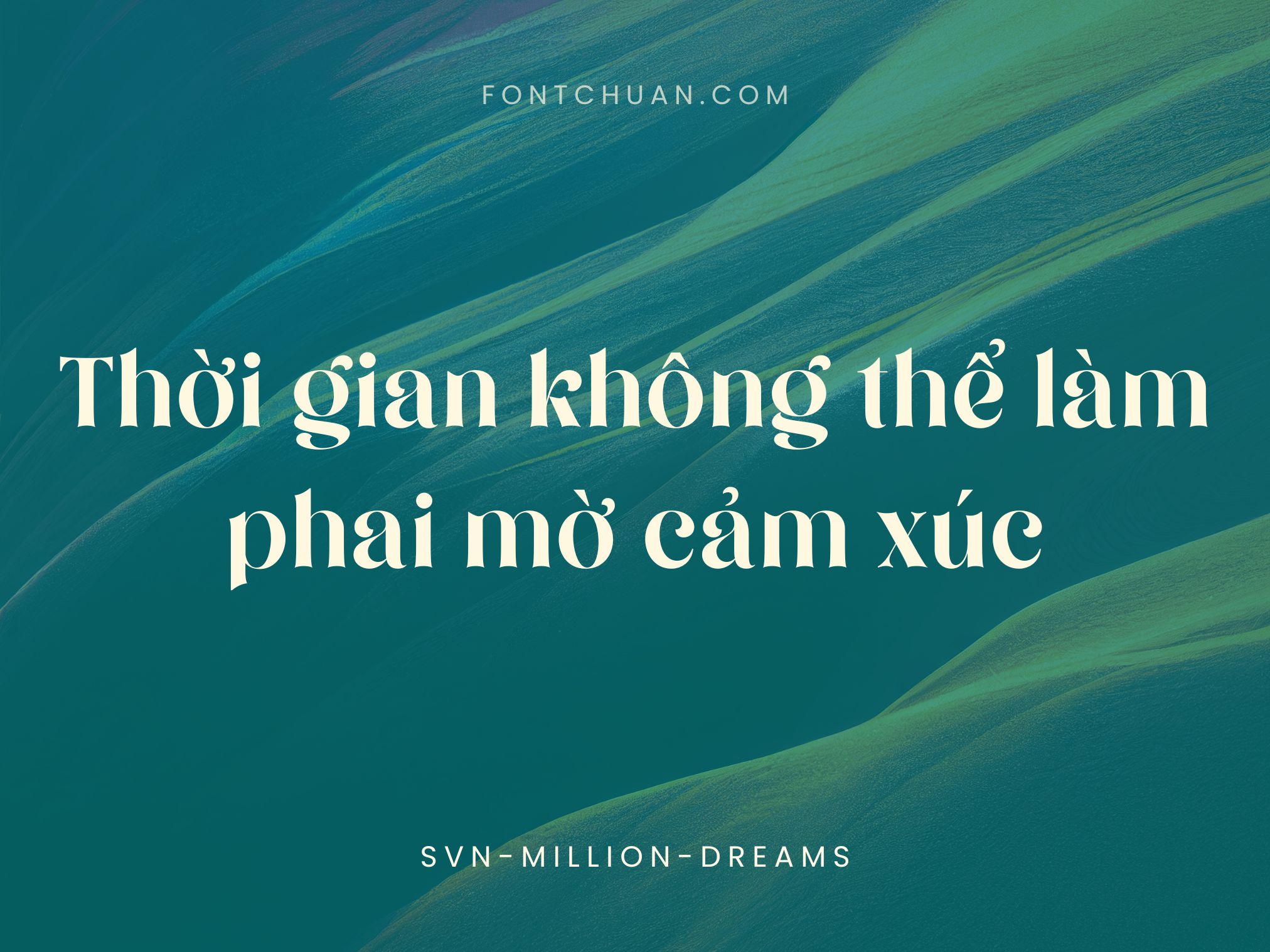
Font SVN Million Dreams là phiên bản Việt hóa của kiểu chữ Million Dreams, được thực hiện bởi STYLEno.1 Fonts. Million Dreams là một kiểu Font Serif mang phong cách vui tươi, nữ tính và hoài cổ, được thiết kế bởi INKSUN. Font này nổi bật với các ký tự thay thế và ligatures độc đáo, tạo nên sự đa dạng và sáng tạo trong thiết kế. Million Dreams bao gồm đầy đủ các ký tự chữ hoa, chữ thường, chữ số và dấu câu, đồng thời hỗ trợ đa ngôn ngữ. Với nét mềm mại và cấu trúc trang nhã, font rất phù hợp cho những dự án mang tính cảm xúc, lãng mạn hoặc mang phong cách cổ điển hiện đại.
SVN Million Dreams lý tưởng cho các thiết kế thiệp cưới, bao bì mỹ phẩm, bìa sách, logo thương hiệu hoặc tiêu đề tạp chí. Các ngành nghề như thiệp cưới, giáo dục và ẩm thực có thể ứng dụng hiệu quả font này để tạo dấu ấn thị giác riêng biệt. Đôi khi font này còn được dùng để làm Font chữ ẩm thực. Bên cạnh đó, font cũng rất phù hợp với các sự kiện như Valentine, Sinh nhật, Tết và các dịp lễ hội khác trong năm.